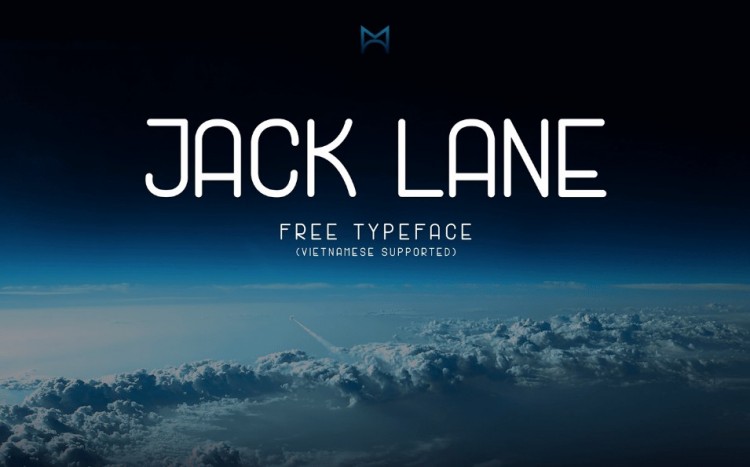
Tải Font tiếng việt Jack Lane miễn phí dành cho thiết kế học đường
Giới thiệu về Font tiếng việt Jack Lane
Trong thế giới thiết kế đồ họa dành cho học sinh và giáo viên, việc lựa chọn một Font Chữ phù hợp đóng vai trò cực kỳ quan trọng. Font tiếng việt Jack Lane nổi lên như một sự lựa chọn hàng đầu nhờ phong cách hiện đại nhưng vẫn giữ được nét thanh lịch cần thiết. Đây là bộ font được các nhà sáng tạo Việt hóa tỉ mỉ, giúp hiển thị đầy đủ các ký tự đặc trưng của tiếng Việt mà không gặp lỗi dấu. Với cấu trúc nét chữ rõ ràng và độ tương phản vừa phải, Jack Lane mang lại cảm giác dễ chịu cho người đọc, rất phù hợp để làm tư liệu giảng dạy hoặc trình bày báo cáo.
Ưu điểm của bộ Font tiếng việt Jack Lane
Tính ứng dụng cao trong môi trường giáo dục
Bộ Font tiếng việt Jack Lane sở hữu thiết kế tối giản nhưng không kém phần sáng tạo. Các bạn học sinh có thể sử dụng font này để thiết kế bìa tiểu luận, làm slide thuyết trình hay trang trí báo tường. Sự chỉn chu trong từng đường nét giúp nội dung bài học trở nên sinh động và thu hút hơn. Đặc biệt, bộ font này hoàn toàn miễn phí cho mục đích cá nhân, giúp tiết kiệm chi phí cho người dùng tại Việt Nam.
Kết luận về bộ font Jack Lane việt hóa